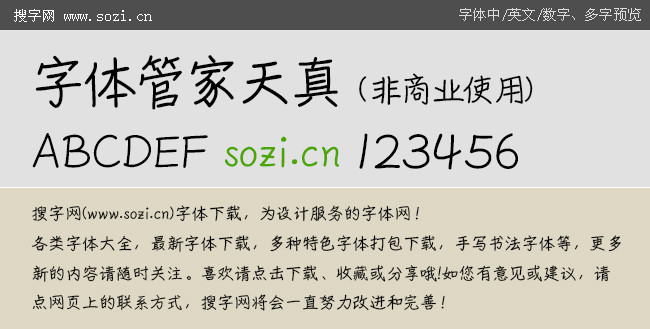
字體管家天真(非商用版)
搜字網(wǎng)給大家提供一款字體管家天真(非商用版)中文字體下載,該字體是一款手寫中文字體,這款字體字形簡潔方正,干凈利落,適合包裝設(shè)計(jì)、書裝設(shè)計(jì)、海報(bào)設(shè)計(jì)等應(yīng)用(此字體為個(gè)人非商用版,商用可以聯(lián)系QQ:1006760504)。